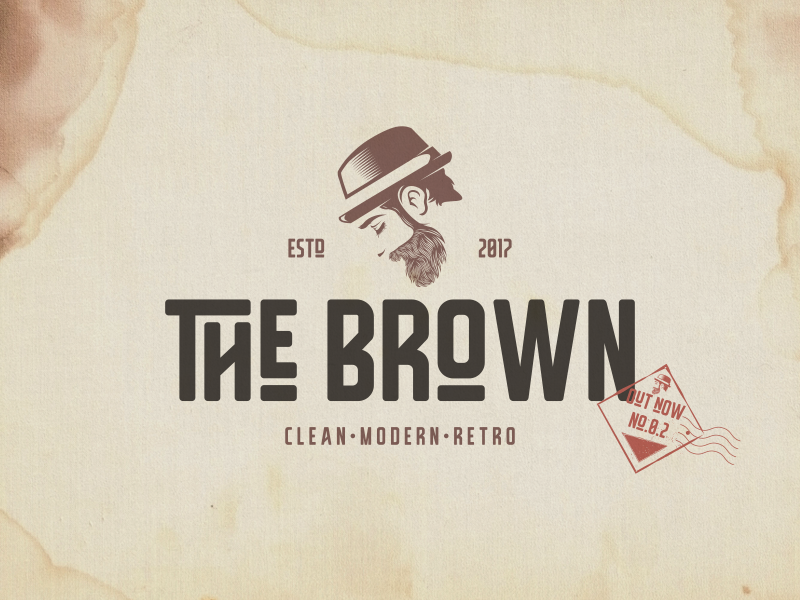
The Brown Typeface – Download Grátis
A The Brown Typeface é uma tipografia sans serif que se destaca por sua elegância moderna e estilo retro clássico. Com seus traços sólidos e limpos, a The Brown é perfeita para quem busca um visual minimalista sem perder o brilho de um design criativo. Ela foi projetada especialmente para facilitar na realização de trabalhos typográficos como logotipos, panfletos, headlines e até mesmo estampas em camisetas. Suas linhas retas e sua paleta de cores neutra permitem que você personalize seu design de acordo com as necessidades do projeto, desde o estilo mais tradicional até aquela inovadora peça criativa que precisará de um toque único. A The Brown é uma ótima escolha para qualquer profissional de design, quer seja iniciante ou experiente. Ela oferece uma versatilidade impressionante sem comprometer em qualidade ou estética.